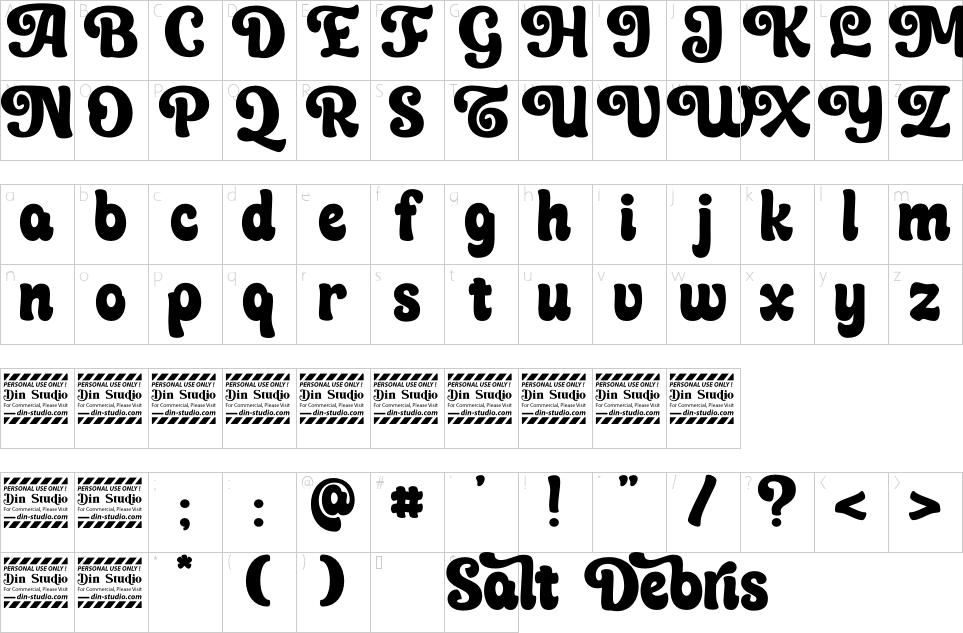
Descubra a fonte Salt Debris, disponível para download gratuitamente tanto para Windows quanto para Mac. Esta elegante e sofisticada fonte foi criada pelo Din Studio e já foi baixada mais de 3.991 vezes. Com uma design envolvente e natural, a Salt Debris é ideal para adicionar um toque único e sofisticado a seus projetos digitais. Adquira a Salt Debris hoje e experimente a qualidade e a variedade desta fonte gratuita. Não hesite, explore e personalize sua identidade visual com a Salt Debris.